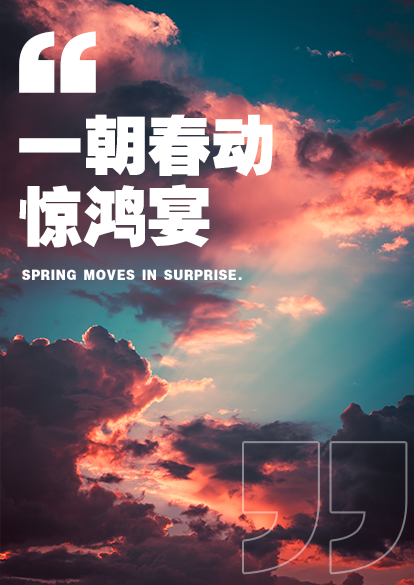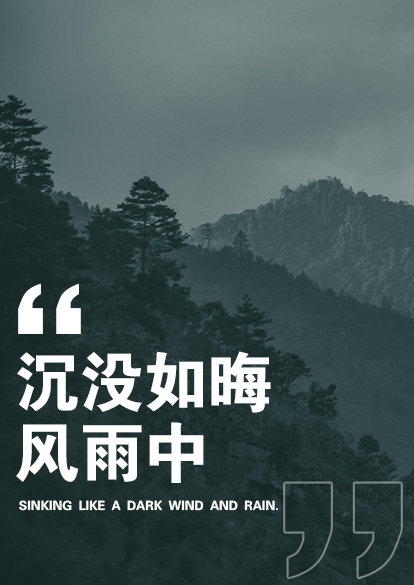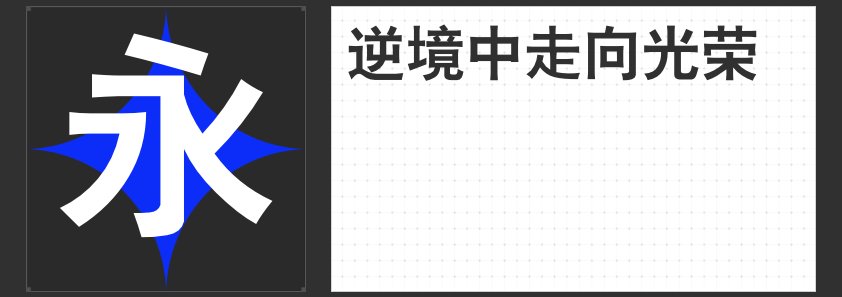
【字体推荐】四款适合标题使用的黑体字体
在设计领域,选择合适的字体对于传达信息和营造氛围至关重要。特别是对于标题这样的重要元素,字体的选择更是不可忽视。今天,将为大家推荐四款非常适合用于标题设计的黑体字体。这些字体以其独特的风格和优秀的可读性,成为了许多设计师的首选。
1.励字励黑简
“励字励黑简”是一款简洁大方的黑体字体。它的线条干净利落,字形饱满且富有力度,适合用于强调和突出重点。无论是用于海报、广告还是网页设计,这款字体都能为标题增添一份现代感和力量感。
2.励字超黑简繁
如果你希望字体既能展现个性又能保持专业感,“励字超黑简繁”将是不错的选择。这款字体结合了现代潮流元素与传统黑体的稳定性,既不失时尚感又具有很好的辨识度。无论是在创意项目还是商业用途中,它都能发挥出色的作用。
3.励字粗黑简繁
对于那些需要强烈视觉冲击力的设计,“励字粗黑简繁”无疑是一个强有力的选择。这款字体的笔画粗壮有力,字形简洁而不失张力。它非常适合用于大型标题、标语或是需要引起关注的地方,能够迅速吸引观众的注意力。
4.励字大黑简繁
最后,我们来看看“励字大黑简繁”。这款字体以其大气磅礴的风格著称,字形宽阔而有力,非常适合用于标题设计。无论是用于海报设计还是品牌标识,它都能够带来强烈的视觉冲击力,让作品脱颖而出。
每款字体都有其独特的风格和适用场景,选择哪一款取决于你的设计需求和个人偏好。无论是追求现代感、潮流感还是力量感,这四款字体都能满足你的需求。